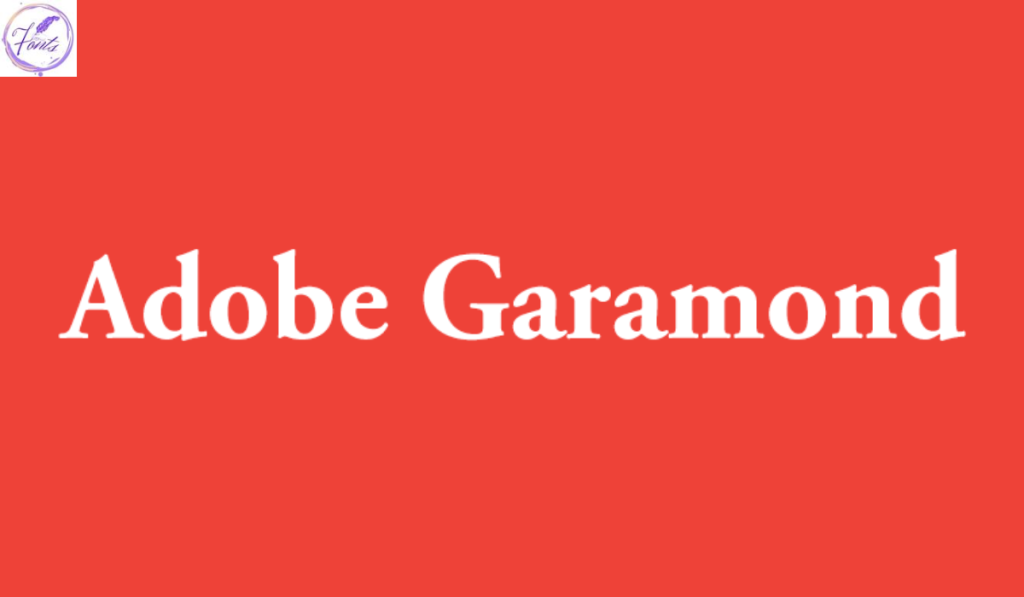
Font Garamond việt hóa
Tác giả: Claude Garamond, Robert Granjon
Ngày phát hành: 1540
Ngôn ngữ: Tiếng Việt, nhiều ngôn ngữ khác
Bộ Font: Garamond
Phân loại: Cổ điển, thanh lịch
Kiểu chữ: Serif (có chân)
Độ dày: Regular, Italic, Bold, Bold Italic
Font garamond việt hóa là bản điều chỉnh tinh tế từ phông chữ Garamond cổ điển, được Claude Garamond, một nhà thiết kế chữ nổi tiếng người Pháp, sáng tạo vào năm 1530. Với các đường nét mượt mà và độ tương phản cao, phiên bản việt hóa này bổ sung bộ ký tự tiếng Việt đầy đủ, giúp nó trở thành lựa chọn lý tưởng cho các ấn phẩm, tạp chí và thiết kế web.